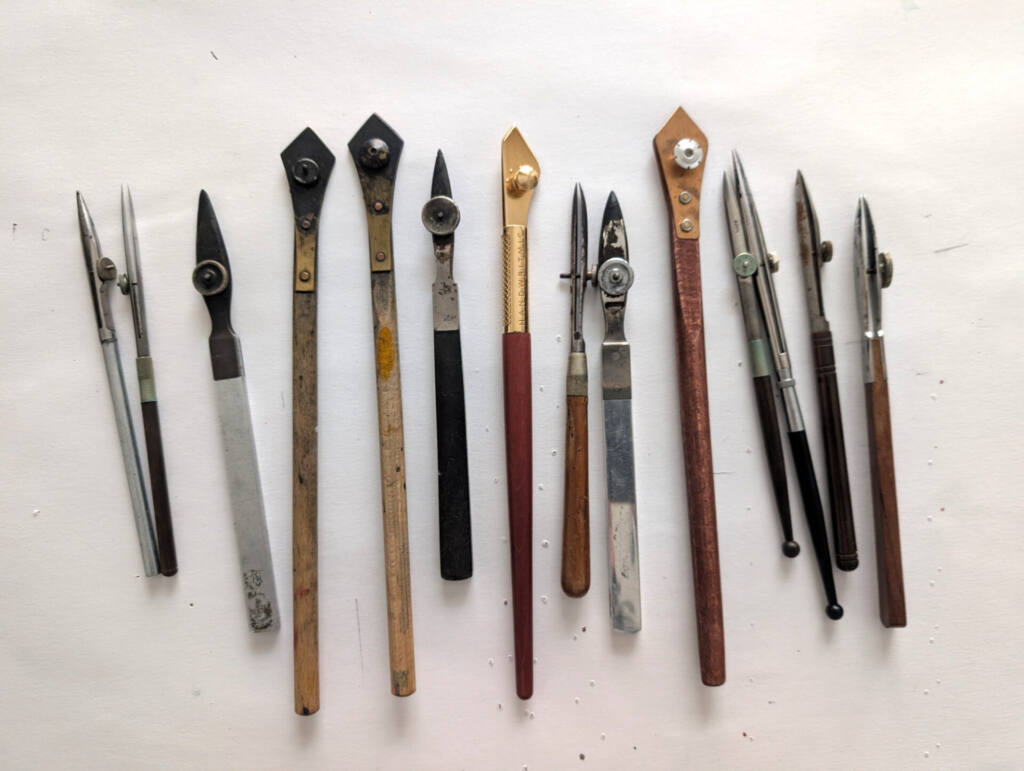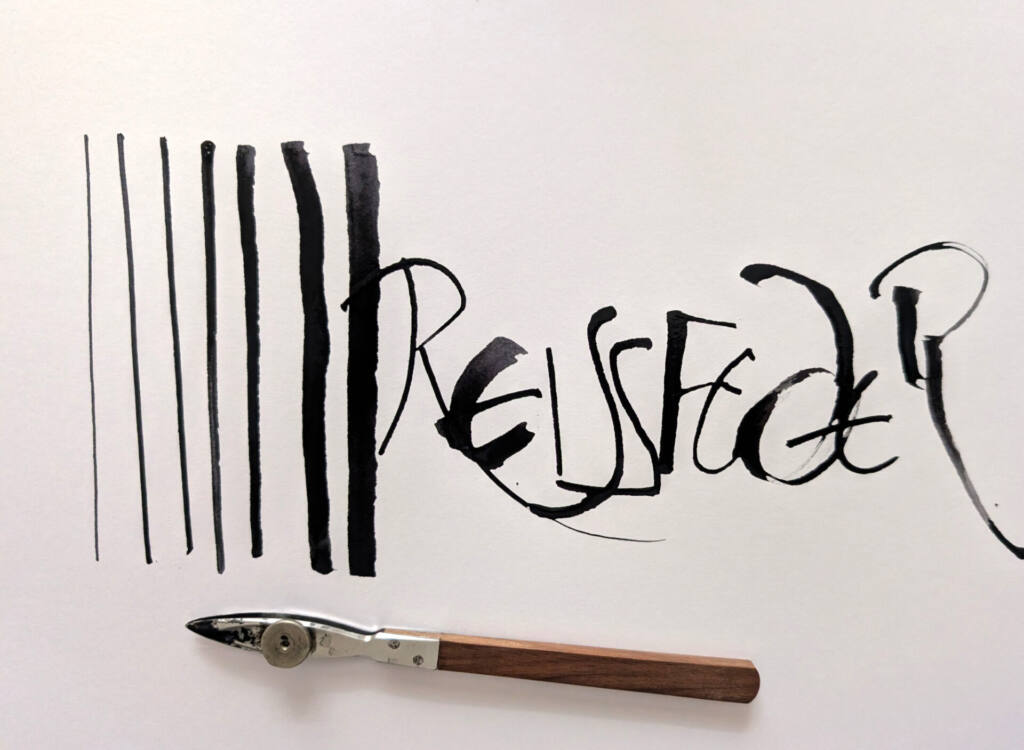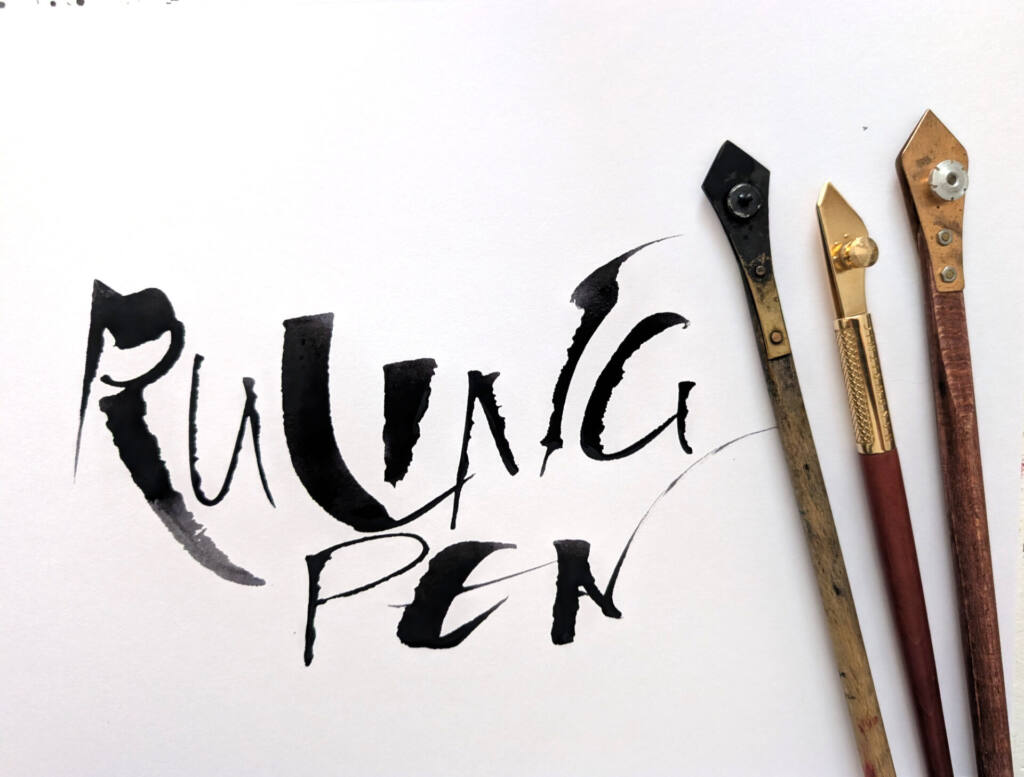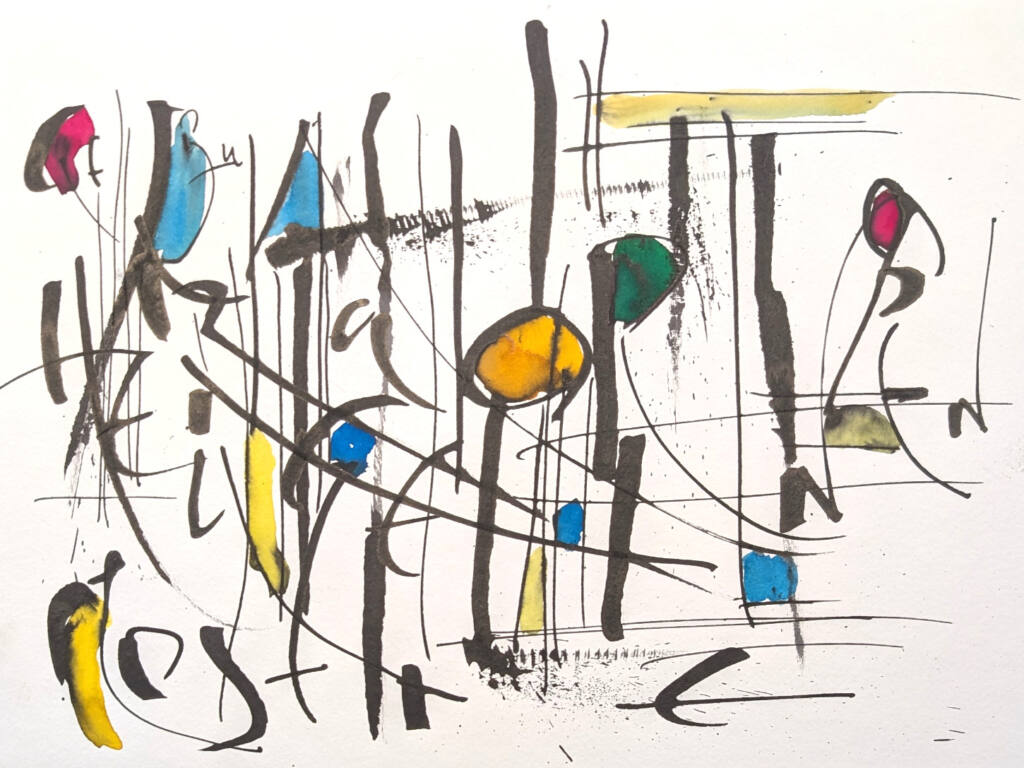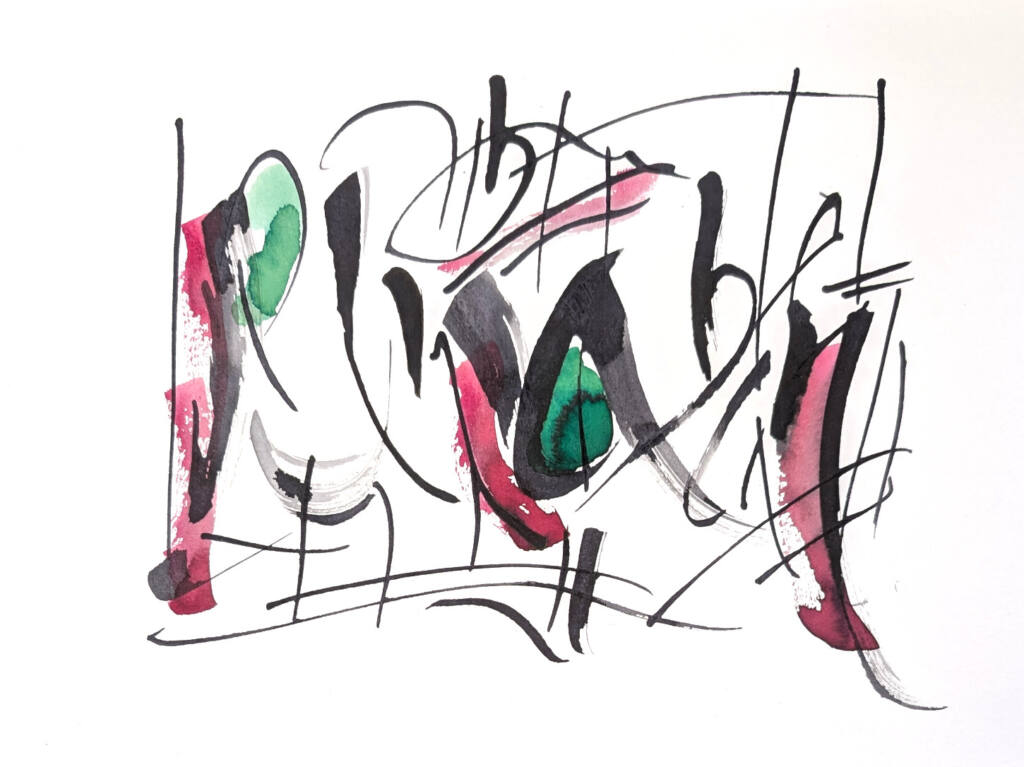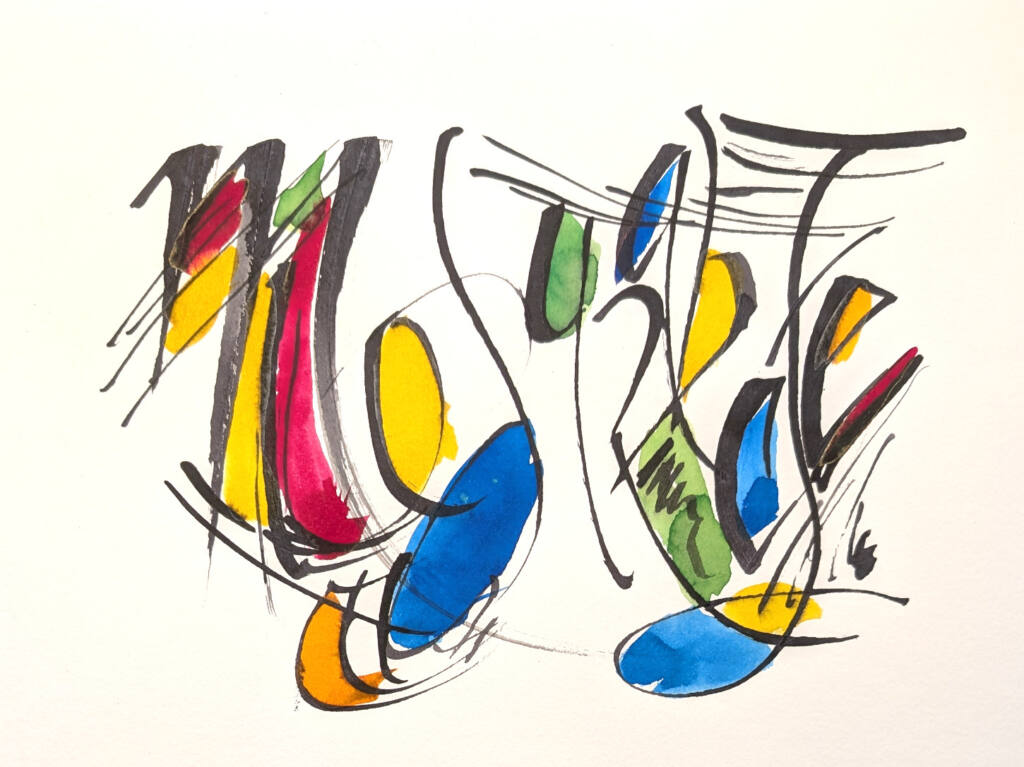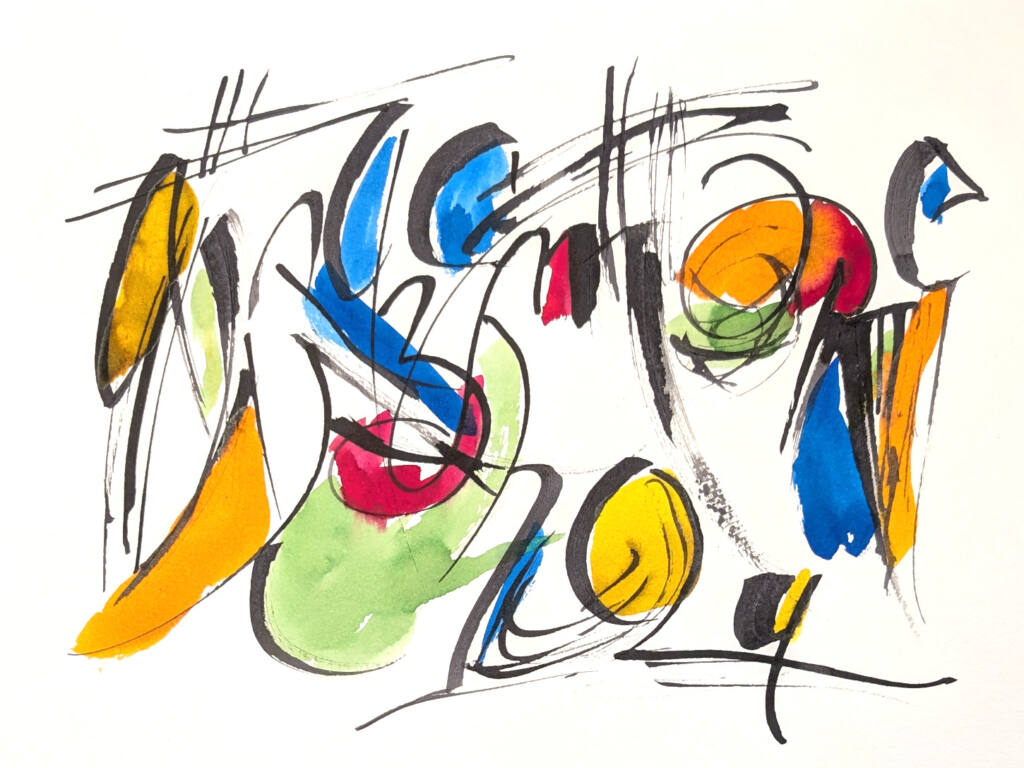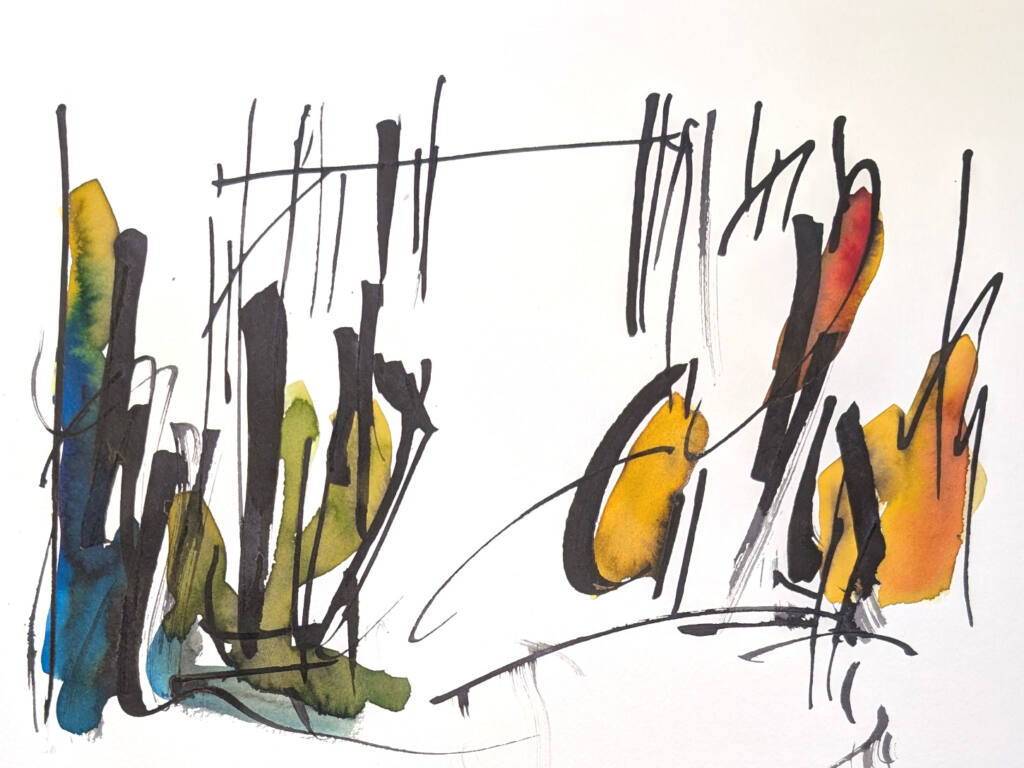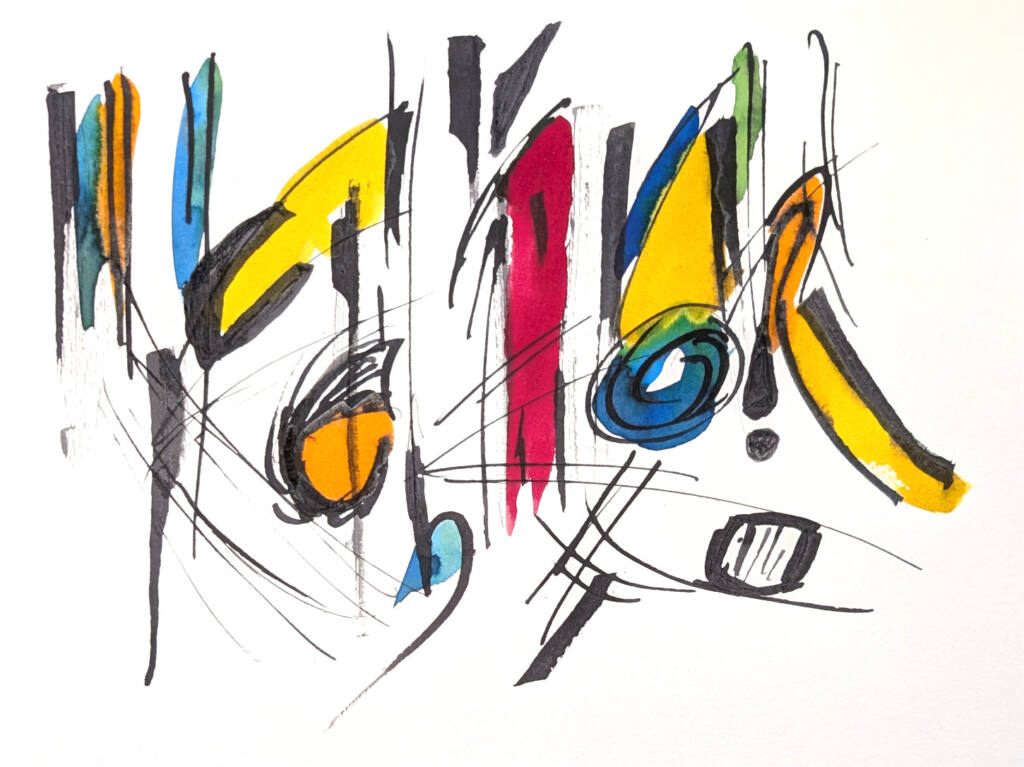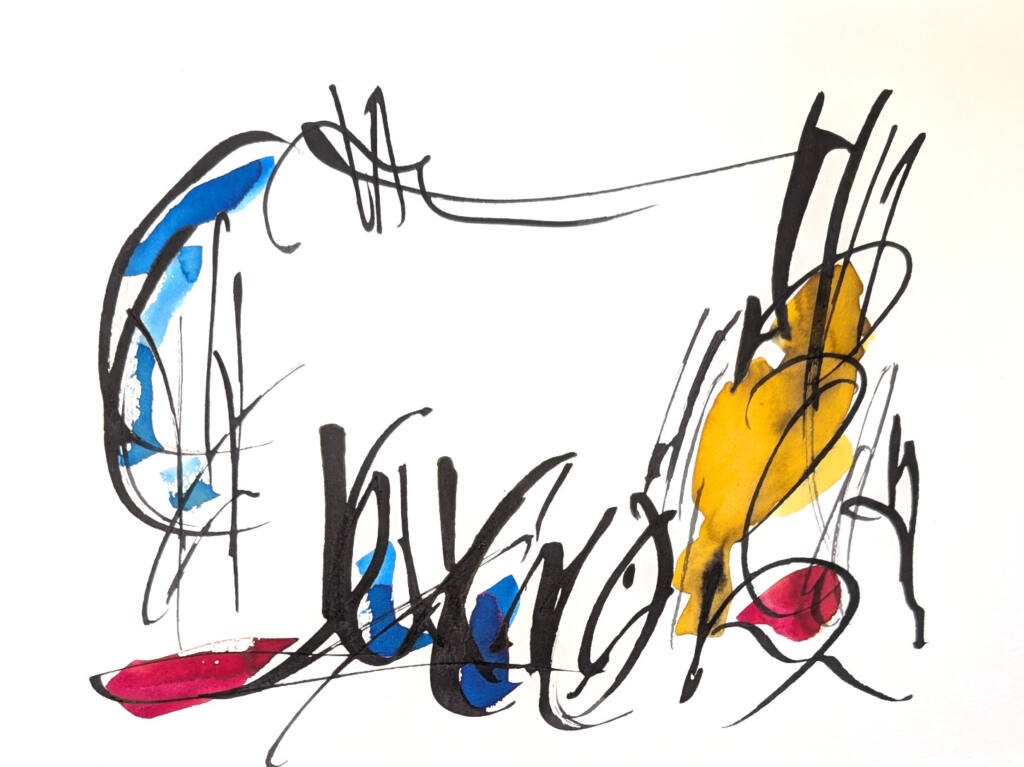
Linienspiele
mit Reissfeder und Ruling Pen
Wenn wir als Schüler einenZirkelkasten bekamen, wunderten wir uns immer über diese seltsame Werkzeug: eine Schraube verstellte den Spalt zwischen den beiden Spitzen. Erst mit der experimentellen Kalligraphie lernten wir die ursprüngliche Bedeutung kennen.
Reissbrett und Reissfeder gehörten früher zum Handwerkszeug des Architekten. Mit Tusche wurden die Entwürfe auf Transparentpapier gezeichnet, dann Reinzeichnung für die Bauherren und Handwerker.
Die Reissfeder - im englischen Ruling Pen - entpuppte sich als vielseitiges Werkzeug für den Kalligraphen. Sie ist auch der Ursprung für die Colafeder.
In diesem Kurs werden wir uns an die Reissfeder heranwagen. Und alles wird wieder Experiment für Linienspiele